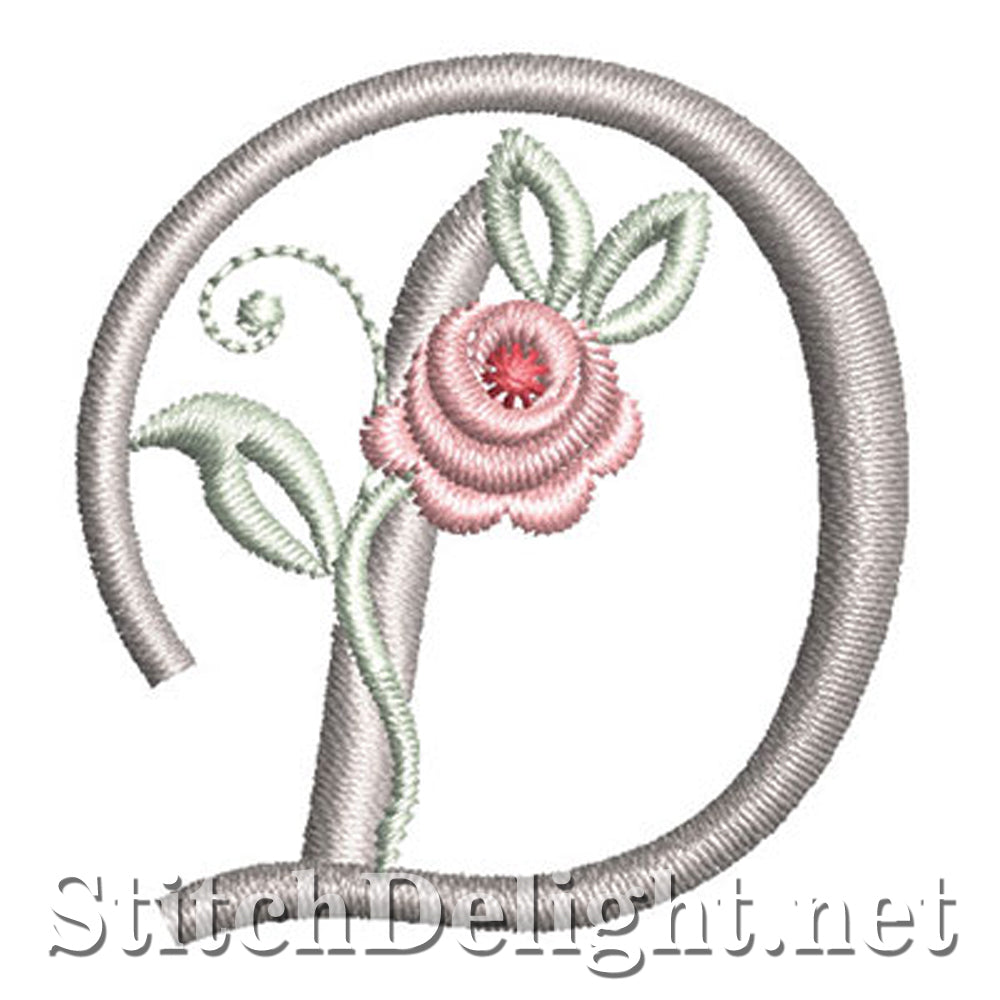
SDS1227 Antiek roos lettertype D
Personaliseer uw project met deze stijlvolle monogramset met delicate roos - ziet er prachtig ton-sur-ton gestikt uit. BX-versie voor Embrilliance-software - Letterhoogte is 1,20 inch / 30 mm